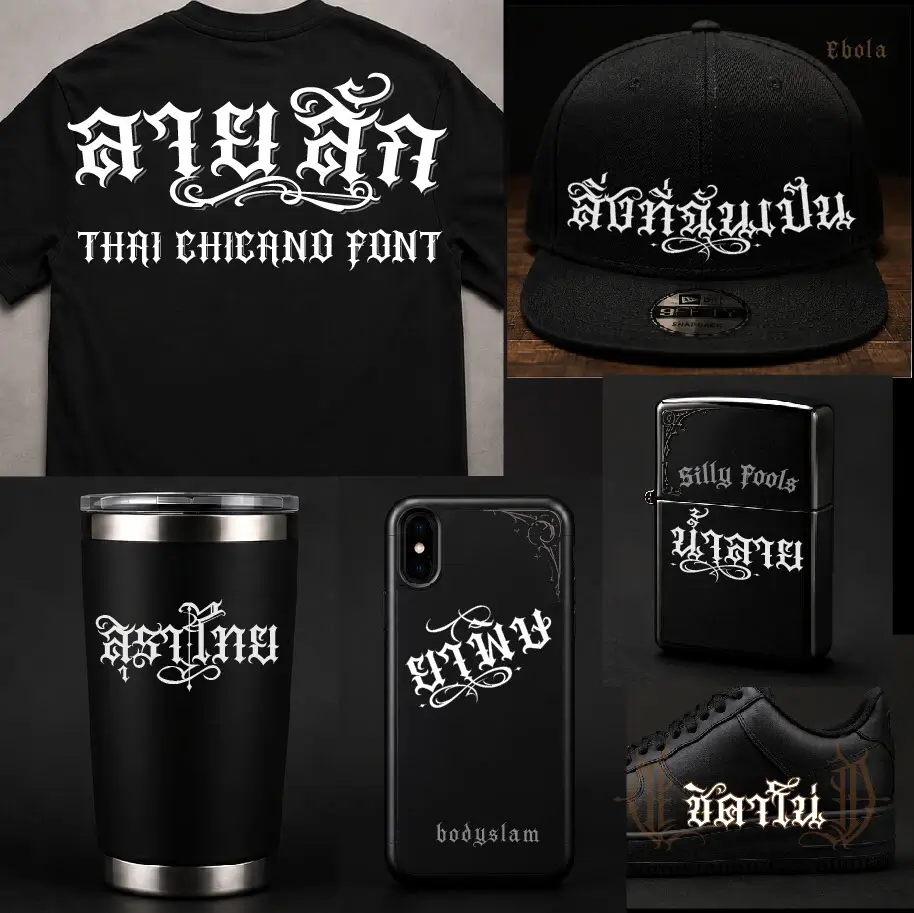
ฟอนต์ เคอาร์ต-ลายสัก (Kart-Rai Sak) – เป็นฟอนต์ที่เขียนเน้นใช้งานแนว #ฟอนต์ลายสัก #tattoofont #thaichicanotattoo เป็นฟอนต์ตัวอย่าง (demo) ครับ
เคอาร์ต-ลายสัก (Kart-Rai Sak)